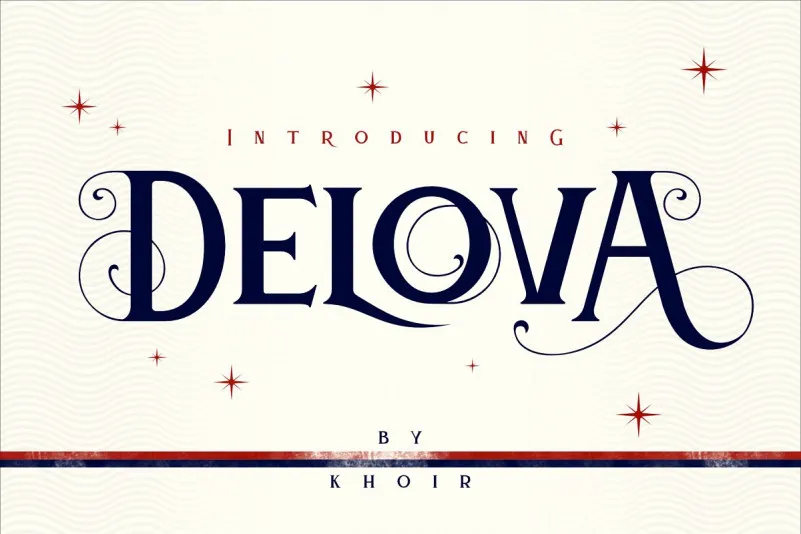
Bem-vindo ao mundo das fontes! Delova é uma fusão fascinante entre serifas tradicionais e a elegância vintage. Esta fonte clássica serif apresenta um toque de modernismo minimalista, oferecendo 104 alternativas para aprimorar suas criações e explorar os infinitos potenciais delas. Delova é perfeita para logos, filmes, livros, embalagens, convites e até mesmo rótulos de marca. Com seu design sofisticado e versátil, você pode personalizar qualquer projeto com a sua graça única. Quer começar? Instale Delova hoje!